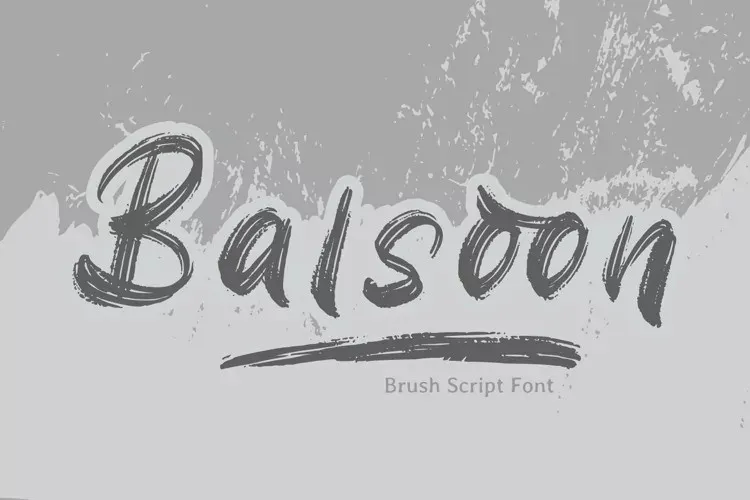
A Balsoon é uma fonte script criada pela Attype Studio, inspirada nos desenhos urbanos com textura vibrante. Essa fonte tem texturas únicas que remetem à arte grafite e letras escritas a mão com esponja, fazendo-a perfeita para uso em designs urbanos e de ruas. Com um forte carácter próprio, ela é perfeitamente adequada para criar design único e vibrante no ambiente urbano. Ideal tanto para adicionar personalidade a sua página web quanto para decorar seus materiais impressos, a Balsoon é uma fonte script que certamente vai chamar atenção e destacar seu projeto de design.